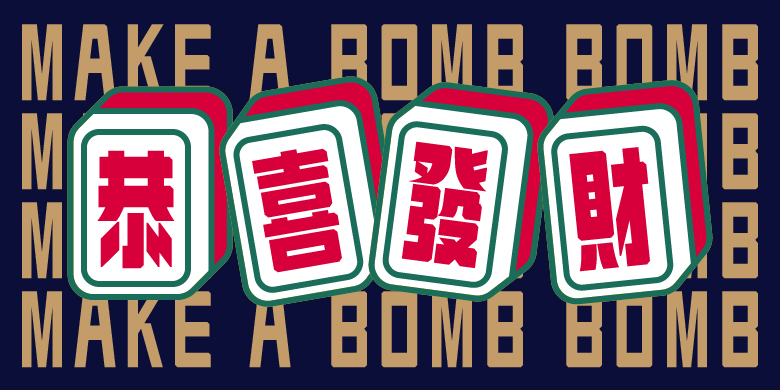
方正复古粗黑
方正复古粗黑,这款字体结构工整、笔画清晰,兼顾美观与易读性,适用于标题、正文、海报、包装、LOGO 等多种场景。字形优雅稳定,风格百搭耐看,适配日常排版与创意设计,让文字呈现更舒适、更具质感。方正复古粗黑一笔一画,皆是细节,以均衡的比例、流畅的线条打造舒适视觉体验,字形端正大气,风格简约现代。无论是商业设计、品牌宣传还是日常排版,都能轻松驾驭,让文字更有格调与力量。方正复古粗黑字体下载。
这是一款与常规黑体设计“横细,竖粗”特点不同的字形,这款字形主打“横粗,竖细”,字形拥有高挑的身形,“横”的笔画边角做了直角切割处理,让笔画处理不显单调。为了避免全直角笔画太过生硬的感觉“撇、捺”笔画使用柔美的曲线代替,整体笔画结构借鉴了老字形的部分特点,融合为一款全新的“方正复古粗黑”。